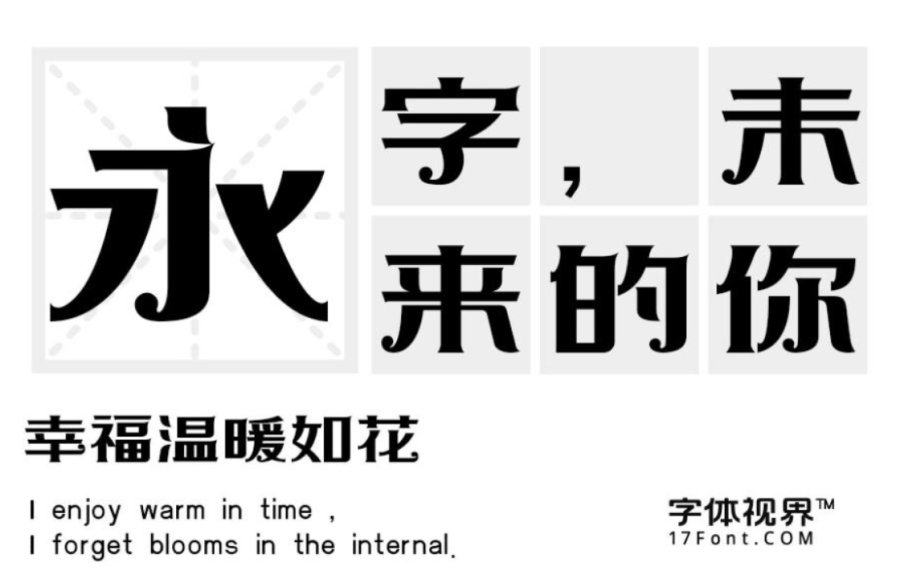
上首车车体|极具创意的高质感字体
上首车车体发布
字体名称:上首车车体
字体类别: 创意黑体
适用场景:封面、广告、屏显、动漫、影视、设计类
上首车车体简介:字体风格稳重呈方块形,字体笔画竖折处细节处理,是此套字库的亮点。字库整体特征坚硬、有力,具有现代、国际化的指向性,适用于搭配标志、广告标语、商业广告等高端属性。
上首车车体预览图展示: